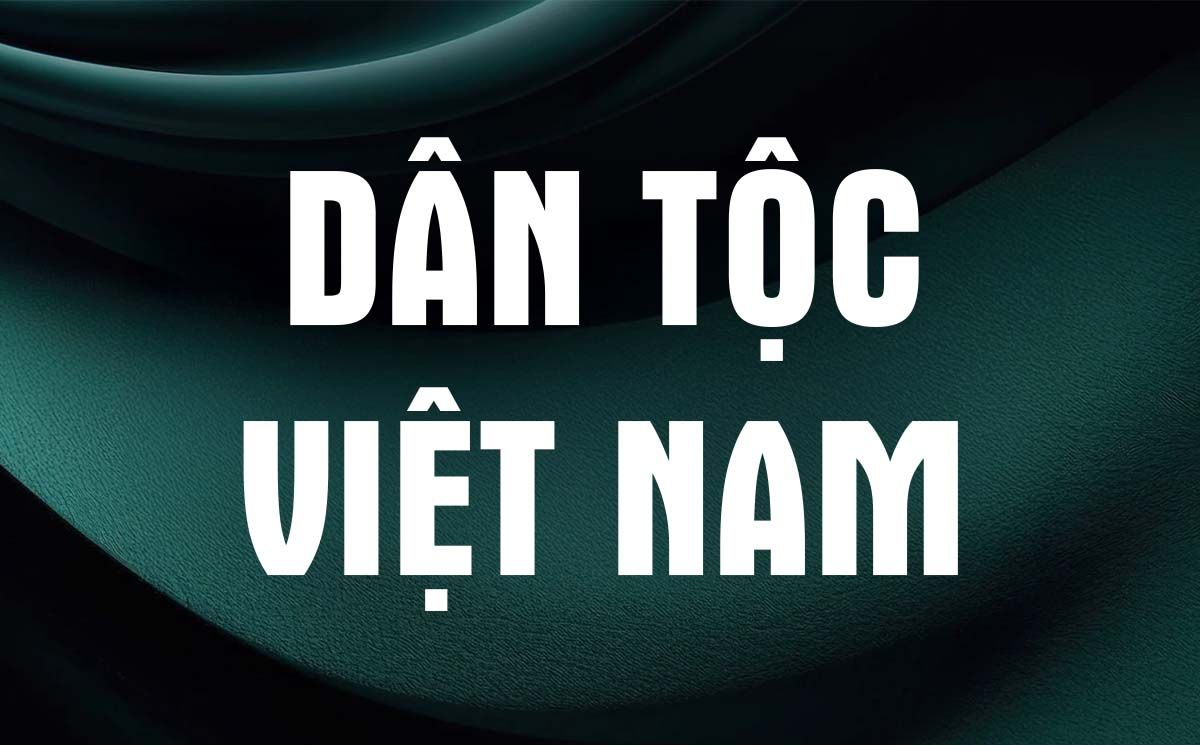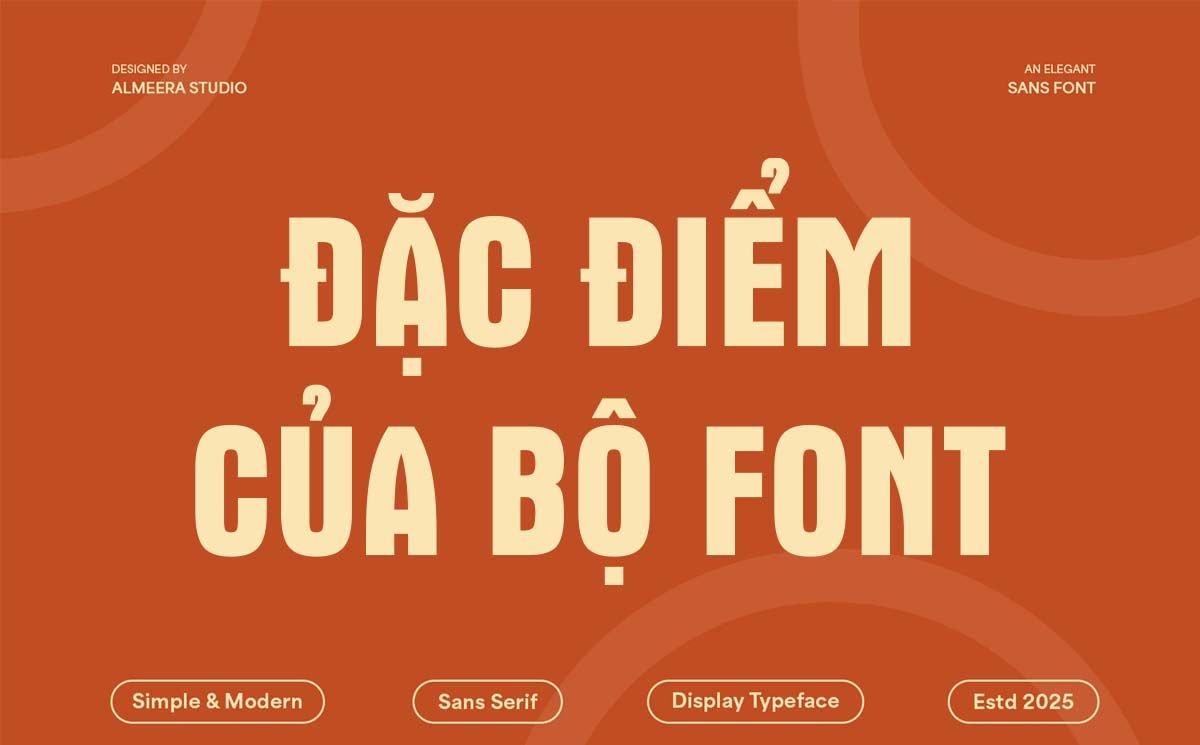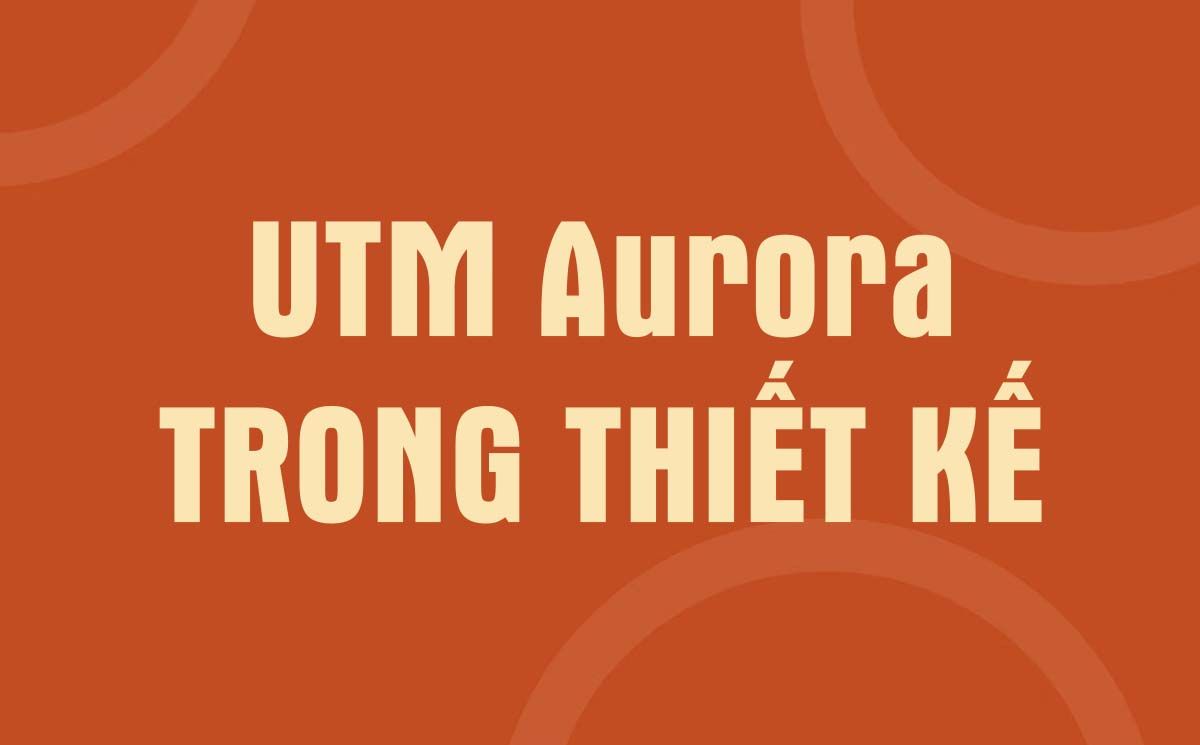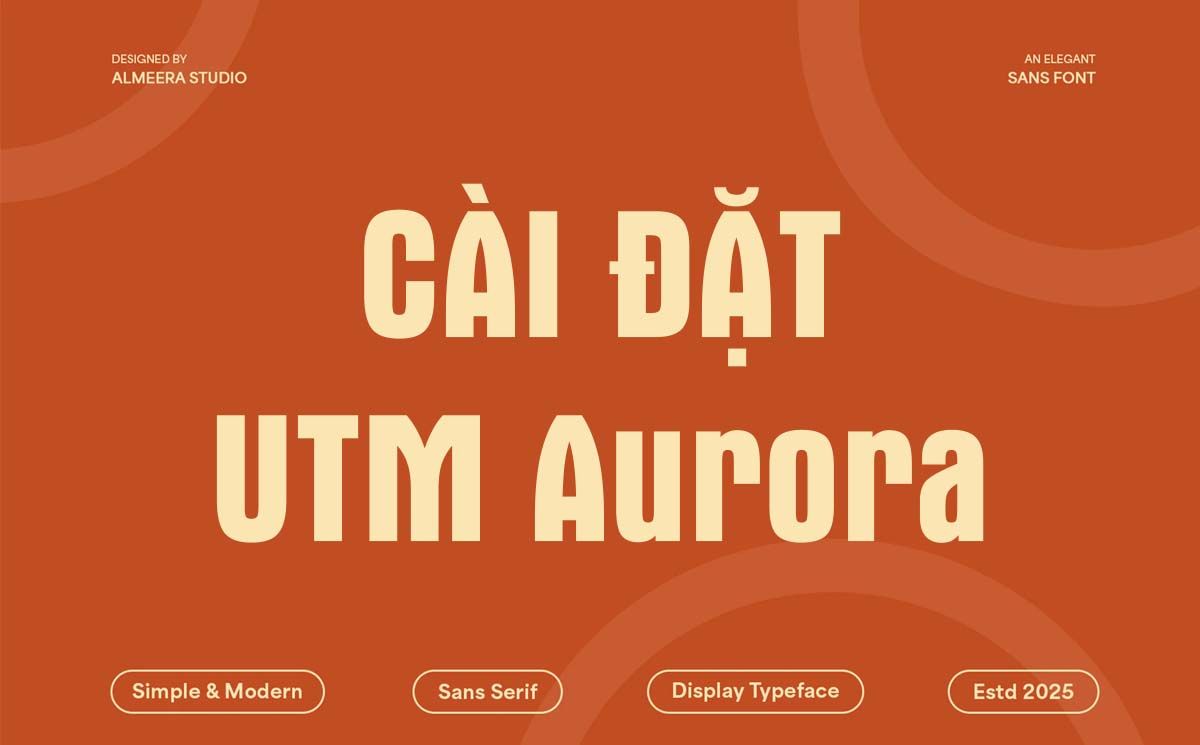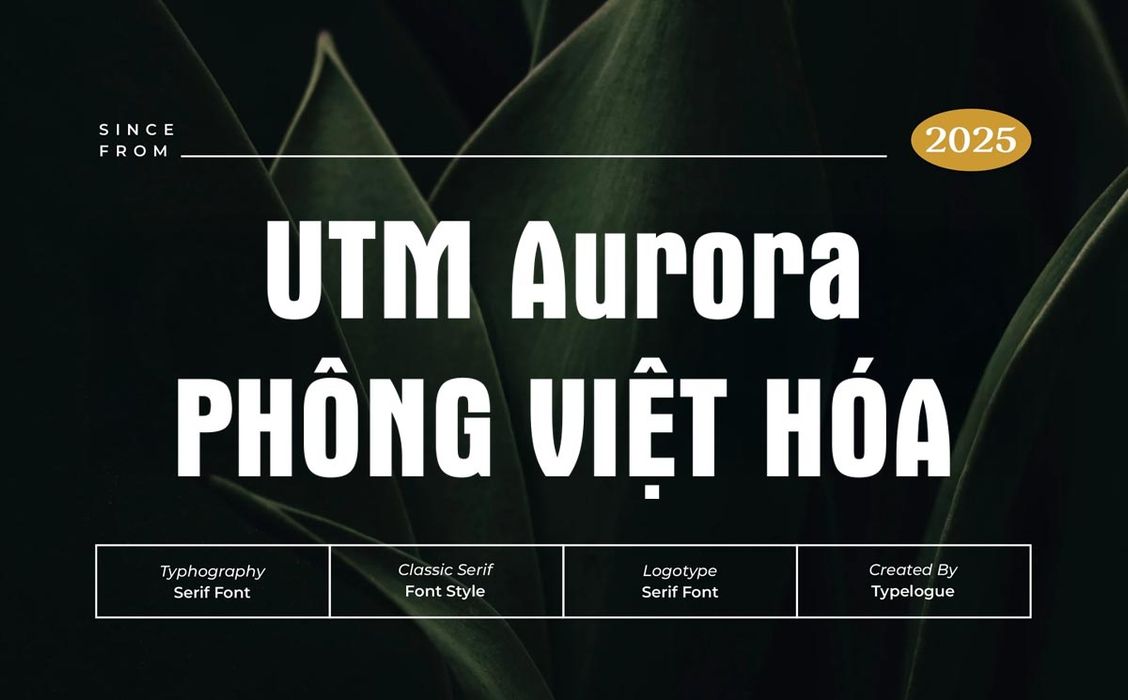
Font UTM Aurora là một trong những bộ font sans-serif tiếng Việt được Việt hóa bởi nhóm Urban Type Management (UTM) – đơn vị uy tín trong lĩnh vực Việt hóa font chữ. Với phong cách hiện đại và cấu trúc dễ đọc, font UTM Aurora mang đến giải pháp trực quan cho các thiết kế cần sự tinh gọn, rõ ràng và chuyên nghiệp.
Nếu bạn đang tìm kiếm một font chữ không chân hiện đại, hỗ trợ tiếng Việt đầy đủ, phù hợp cho cả thiết kế số lẫn in ấn – UTM Aurora là cái tên rất đáng để thử.
Font UTM Aurora thuộc nhóm sans-serif – không chân, gọn gàng và hiện đại. Các ký tự có tỷ lệ hài hòa, đường nét sắc sảo với độ dày vừa phải, giúp hiển thị tốt cả tiêu đề lẫn nội dung văn bản dài. Thiết kế này mang lại trải nghiệm đọc thoải mái, đặc biệt trên các nền tảng số như website hoặc app.
Nhờ sự cân đối và tối giản, UTM Aurora có thể ứng dụng linh hoạt trong nhiều lĩnh vực:
Trong giao diện web, ứng dụng và dashboard, font giúp hiển thị rõ ràng, tối ưu trải nghiệm người dùng.
Khi dùng cho slide thuyết trình và tài liệu văn phòng, nó mang lại cảm giác chỉnh chu, chuyên nghiệp và nhất quán.
Đối với poster sự kiện, brochure doanh nghiệp, UTM Aurora giúp truyền tải nội dung sắc nét mà không làm rối mắt.
Trong các ấn phẩm số như tạp chí điện tử hoặc tài liệu e-learning, font giữ được khả năng đọc tốt trên nhiều thiết bị.
Với các thiết kế social media, UTM Aurora thể hiện thông điệp một cách rõ ràng, trẻ trung, dễ tiếp cận người xem.
Thiết kế gốc: Font Aurora là một kiểu chữ sans-serif quốc tế, có nhiều biến thể.
Việt hóa bởi: Urban Type Management (UTM) – nhóm thiết kế chuyên Việt hóa font nhằm tối ưu cho nhu cầu nội dung tiếng Việt.
Trong kho tàng font chữ Việt hóa đẹp, UTM Aurora nổi bật nhờ sự kết hợp giữa thiết kế thanh thoát, khả năng đọc tốt và độ ứng dụng cao. Nếu bạn đang tìm một font sans-serif tiếng Việt hiện đại, dễ dùng và dễ tích hợp vào mọi dự án – từ thiết kế kỹ thuật số đến văn bản in ấn – thì đây chắc chắn là lựa chọn đáng tin cậy.